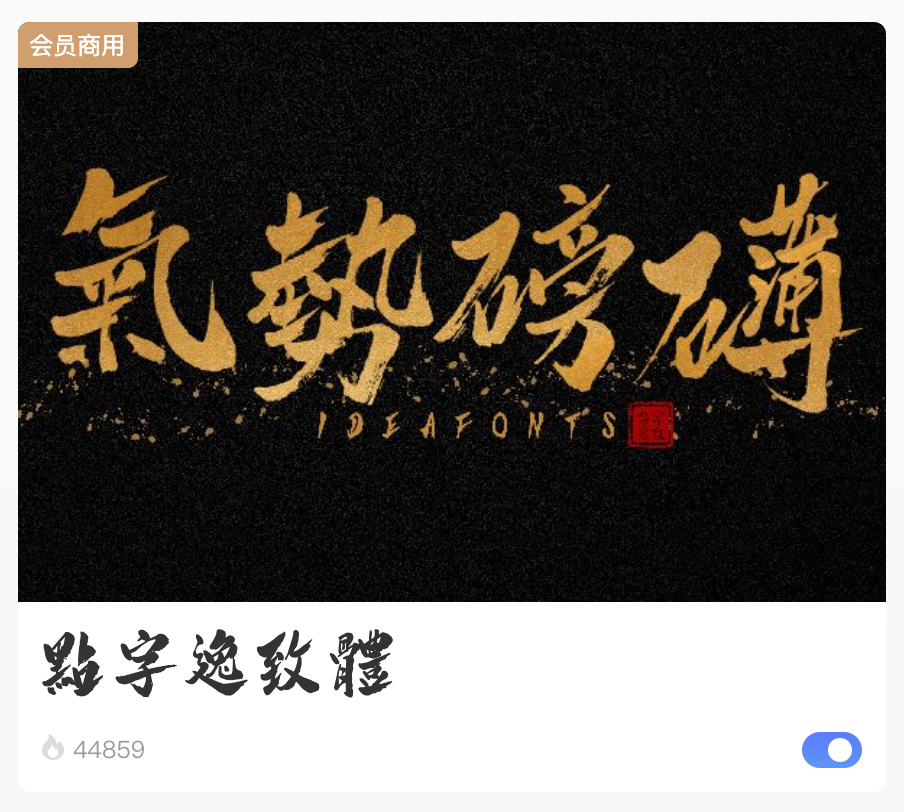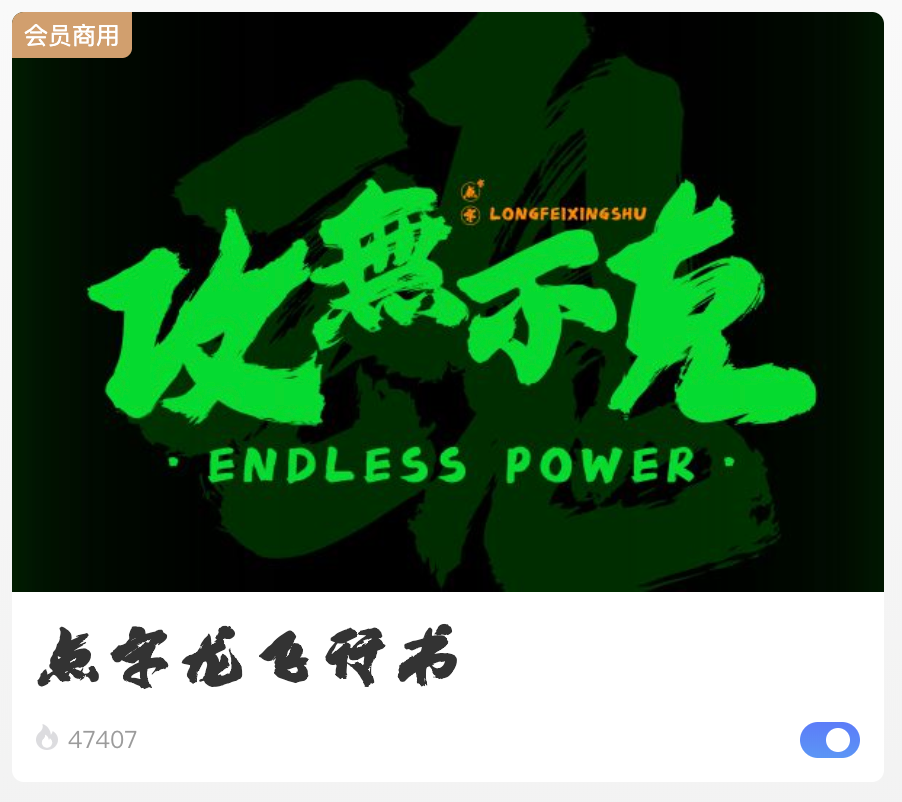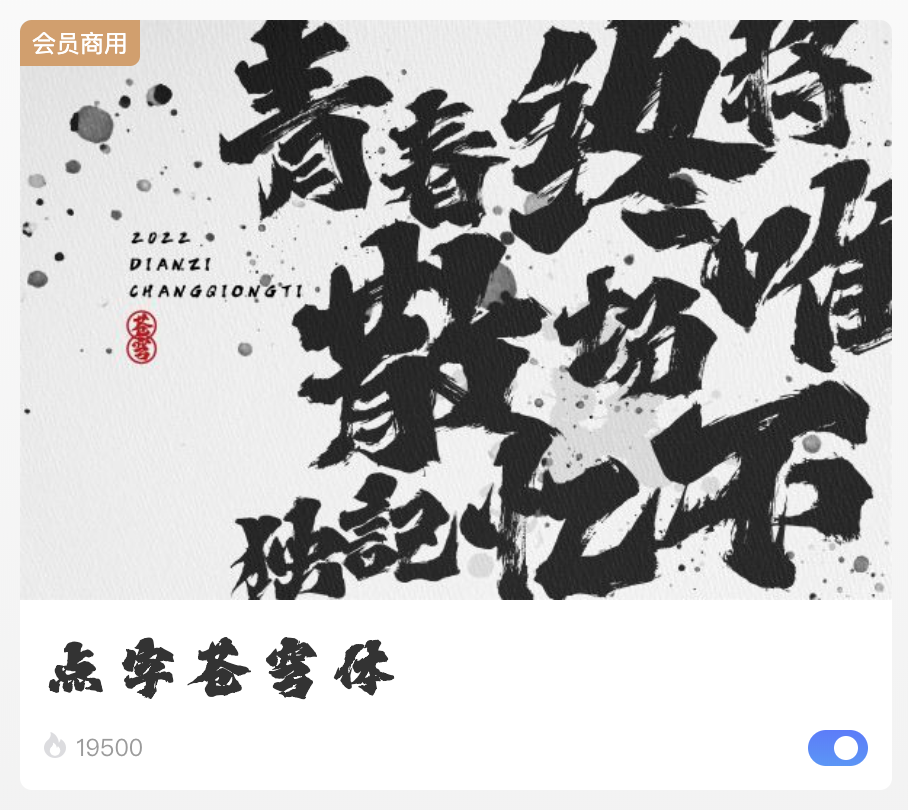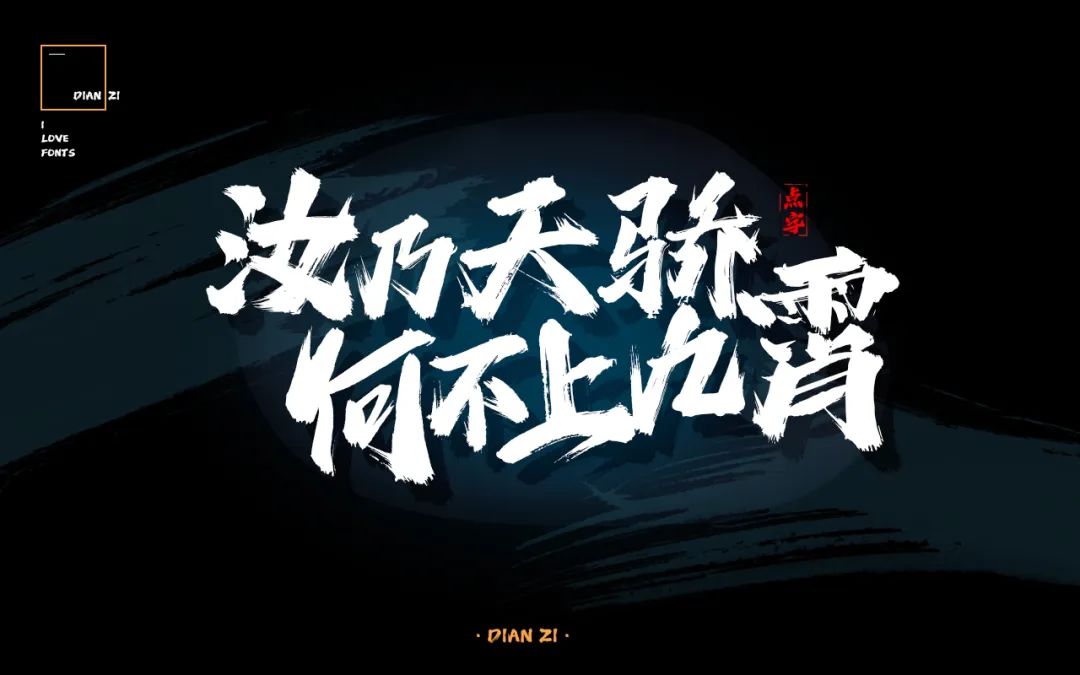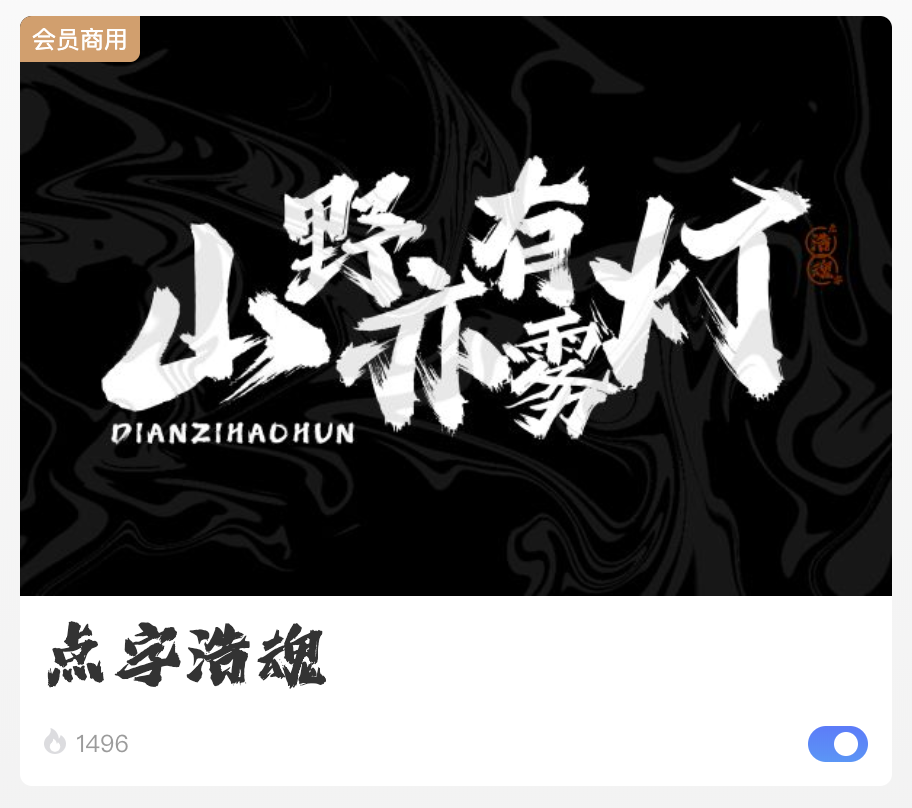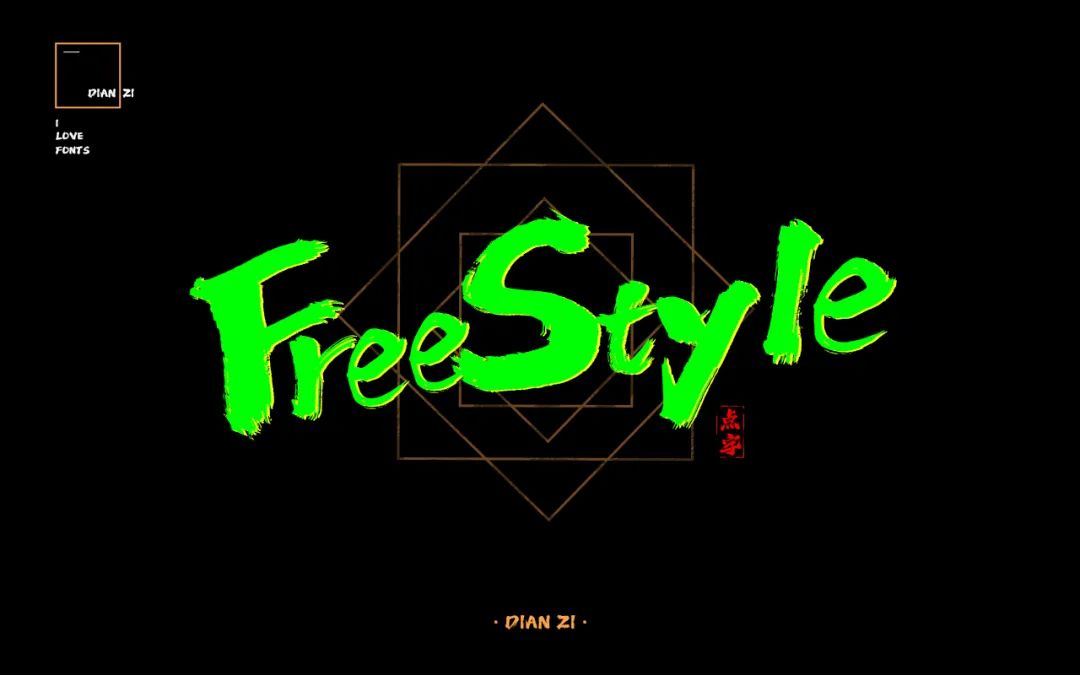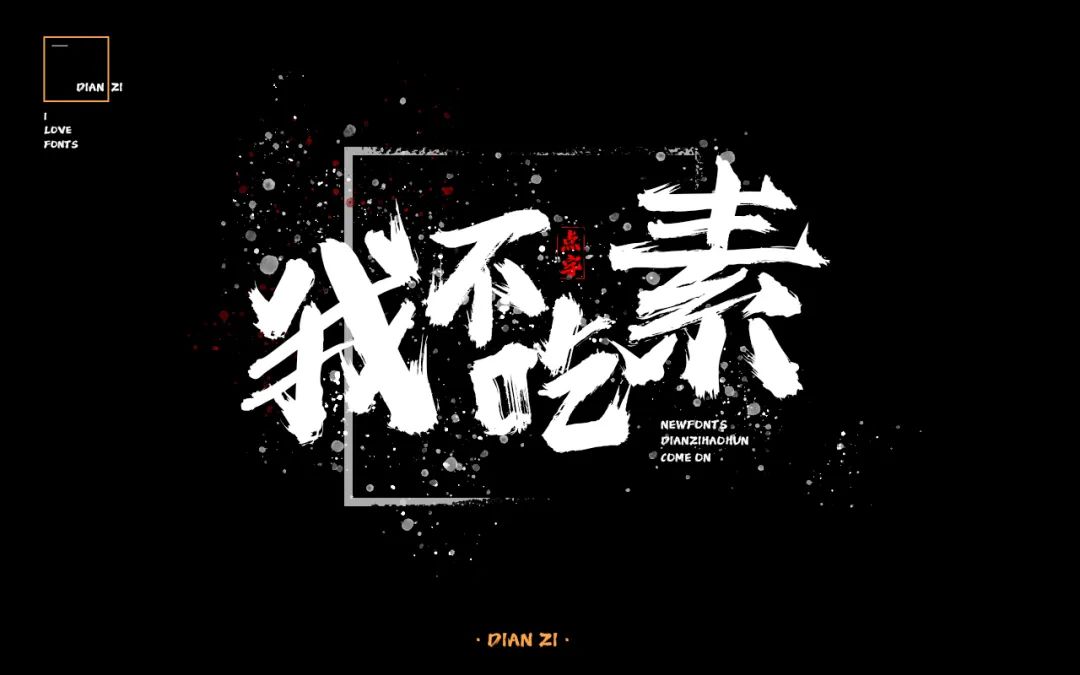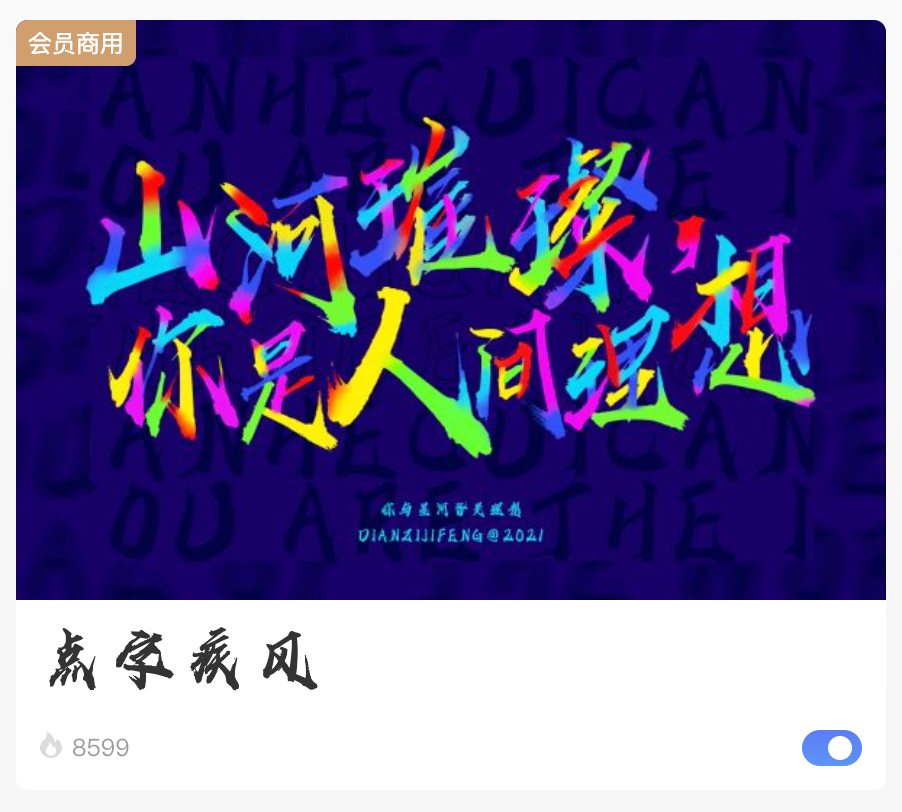
啊啊啊,这些手写字太蛊了~
他们之所以能击中你的心巴,让你欲罢不能,不外乎都掌握了以下几个流量密码。
颜值YYDS
如果说霸总题材永不过时,有一点很关键,那就是颜值,只要一眼沉沦,那你说什么都对,比如最新上线的点字浩魂:
武力值爆表
除了颜值,他们还都拥有超强的武力值,这溢出屏幕的安全感,谁不想被拥入怀中?看看点字苍穹体,你就懂了。
细节撩人
颜值+武力值都无可挑剔,但如果是个妥妥的钢铁直男,也不能俘获迷妹们的芳心,需要撩人于无形的细节,比如点字逸致体:
疯批带感
有了前面的光环加持,就算后面陷入疯狂,也不再是缺点,而是你爱他的理由,就像脱缰的点字龙飞行书。
执念很深
只要执着于该执着的,放弃不该执着的,你的执念就有一种刻入骨髓的魅力,比如点字疾风:
虽然“星沉诀”已经结束了,但他们留下的流量密码,还值得我回味10086遍,我宣布,以上字体已成功蛊到了我~